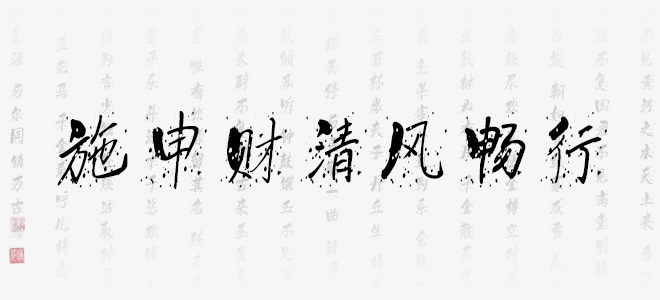
施申財(cái)清風(fēng)暢行是一款極具個(gè)性的書法藝術(shù)字體,點(diǎn)墨背景讓字體擁有了風(fēng)吹之感。字體線條粗細(xì)適中,筆畫隨性,結(jié)構(gòu)灑脫自在,具有很好的視覺效果,適合于文化類的宣傳設(shè)計(jì)、商業(yè)類品牌的廣告和產(chǎn)品包裝設(shè)計(jì)以及個(gè)性化文字排版等較多場(chǎng)景。
施申財(cái)清風(fēng)暢行